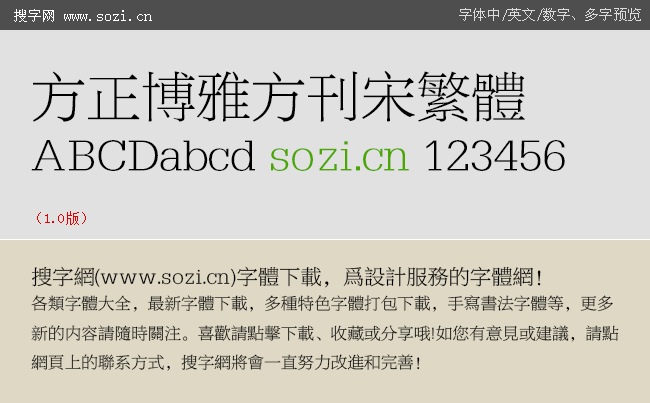
方正博雅方刊宋繁體(FZBYFKSFW)
搜字網(wǎng)提供一款方正博雅方刊宋繁體中文字體下載,方正博雅刊宋是一款清秀大方的中文簡(jiǎn)體字體,非常端正,可廣泛應(yīng)用于圖書(shū)印刷、產(chǎn)品包裝、平面廣告等行業(yè)等廣告設(shè)計(jì)場(chǎng)合使用。